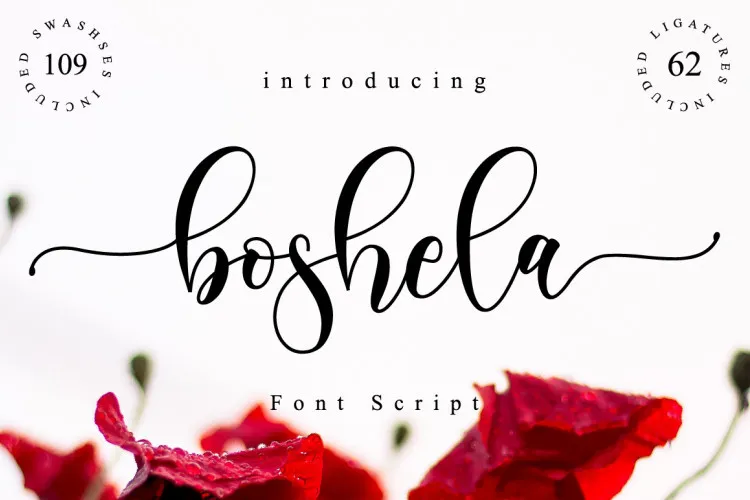
Boshela Script é uma elegante fonte de estilo moderno com uma característica fascinante que combina influências do penhoar de latão com tipografia contemporânea, resultando num deslizamento leve na linha de base e um toque clássico e refinado. Essa fonte foi projetada para atender a necessidades específicas em design gráfico, como logomarcas, marcas de marca, convites, cartões postais, designs de casamentos, compartilhamento nas redes sociais, entre outros projetos que requerem um toque manuscrito. Seu aspecto sofisticado e moderno a torna uma escolha ótima para quem busca combinar elegância com inovação na criação de identidades visuais, gráficos corporativos e elementos decorativos em projetos digitais ou impressos. Boshela Script é ideal para aqueles que procuram um toque único para suas obras, transformando qualquer projeto em algo autêntico e memorável.